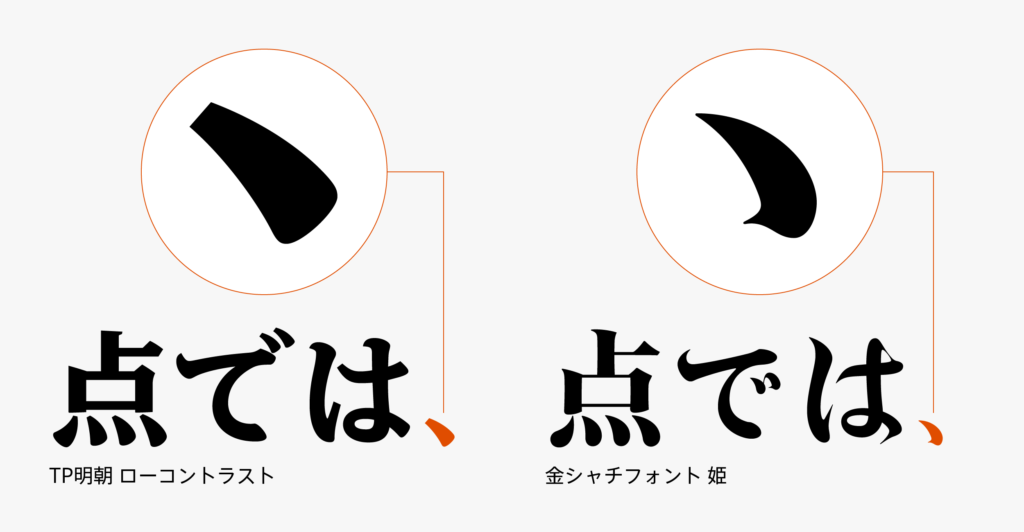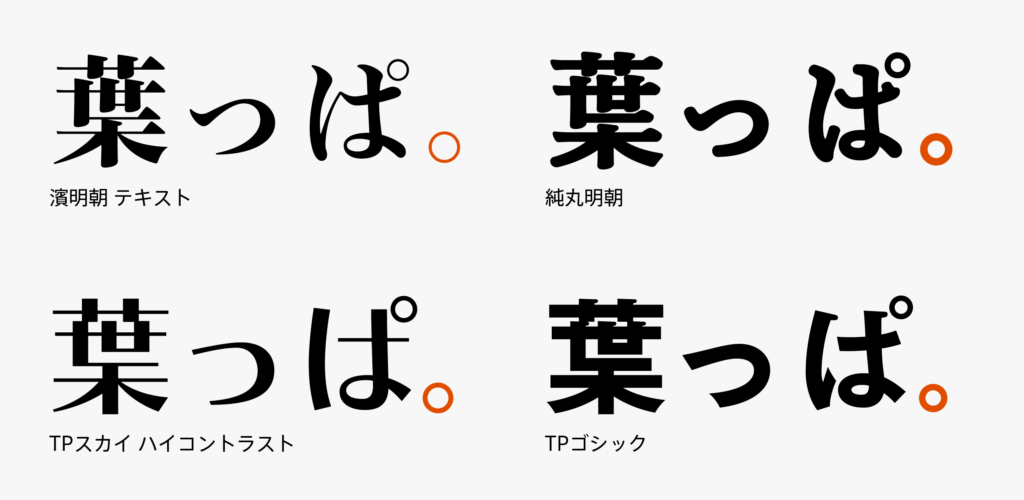
和文約物01「句読点」
約物とは、組版で使われる文字数字以外の記号類(句読点や括弧など)の総称です。このシリーズでは約物の中でも主に和文と一緒に制作するグリフの制作ポイントや小話を紹介していきます。今回は使用頻度の高い約物である句読点(。、)です。
テンこと読点(、)は仮名や漢字の点とデザインを合わせます。少し四角っぽいTP明朝 ローコントラストの点や、次の文字への筆脈を思わせる金シャチフォント 姫の点など、読点だけでもフォントの個性を感じられることがあります。
マルこと句点(。)は多くの場合、コンパスで書いたような正円でデザインされます。仮名や漢字には正円のパーツがないので、私は句点の形状を奇妙に感じることがあります。同じく半濁点(゜)も基本的に正円ですね。ご存知の方も多いかもしれませんが、日本語には長らく句読点や濁点半濁点がなく、現在のように使用されるのは明治時代になってからでした。仮名や漢字との歴史の違いに突然現れた正円の謎を解くカギがありそうです。